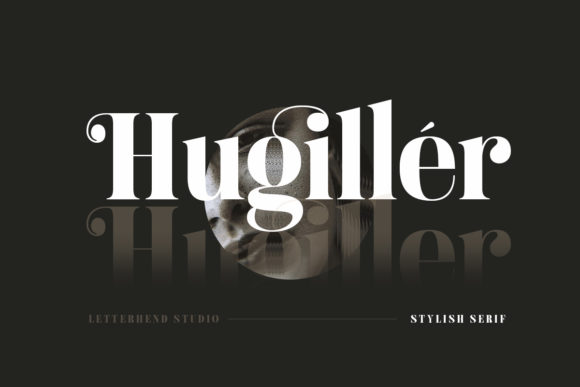
Hugiller - это стильный, жирный шрифт с засечками.
Его можно использовать для различных целей, таких как логотипы, свадебные приглашения, заголовки, футболки, бланки, вывески, этикетки, новости, плакаты, значки и многое другое.